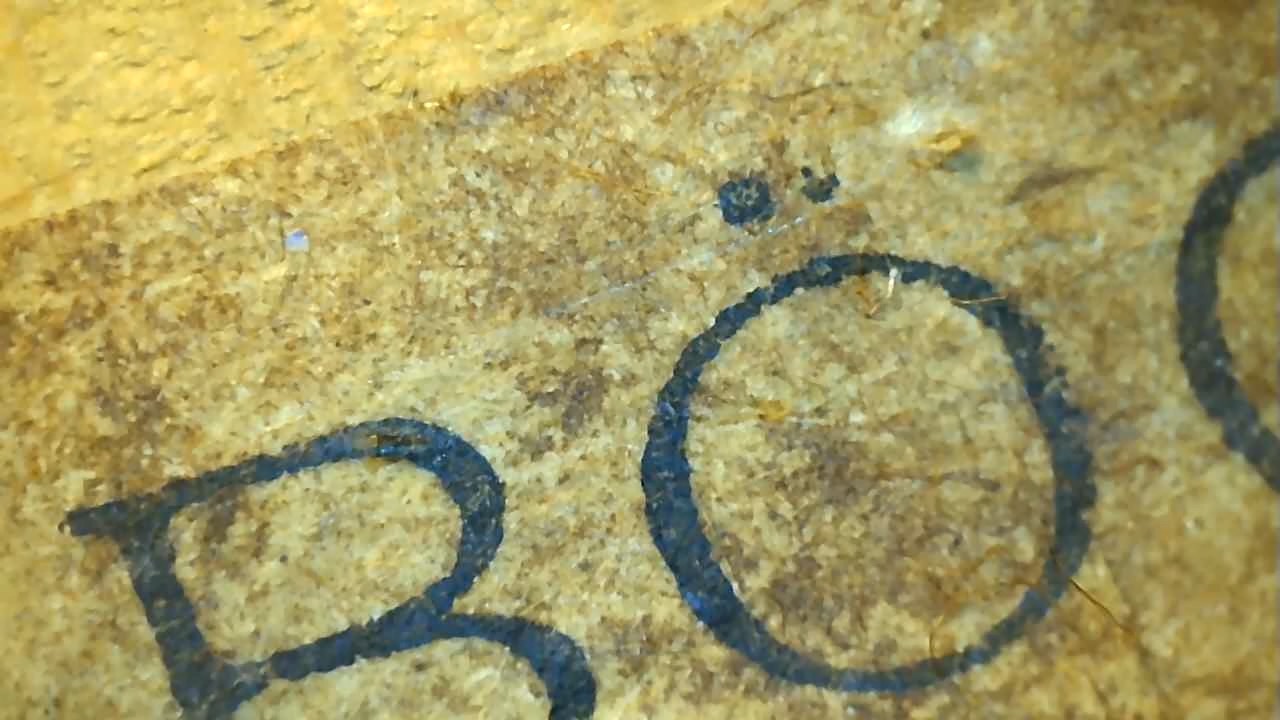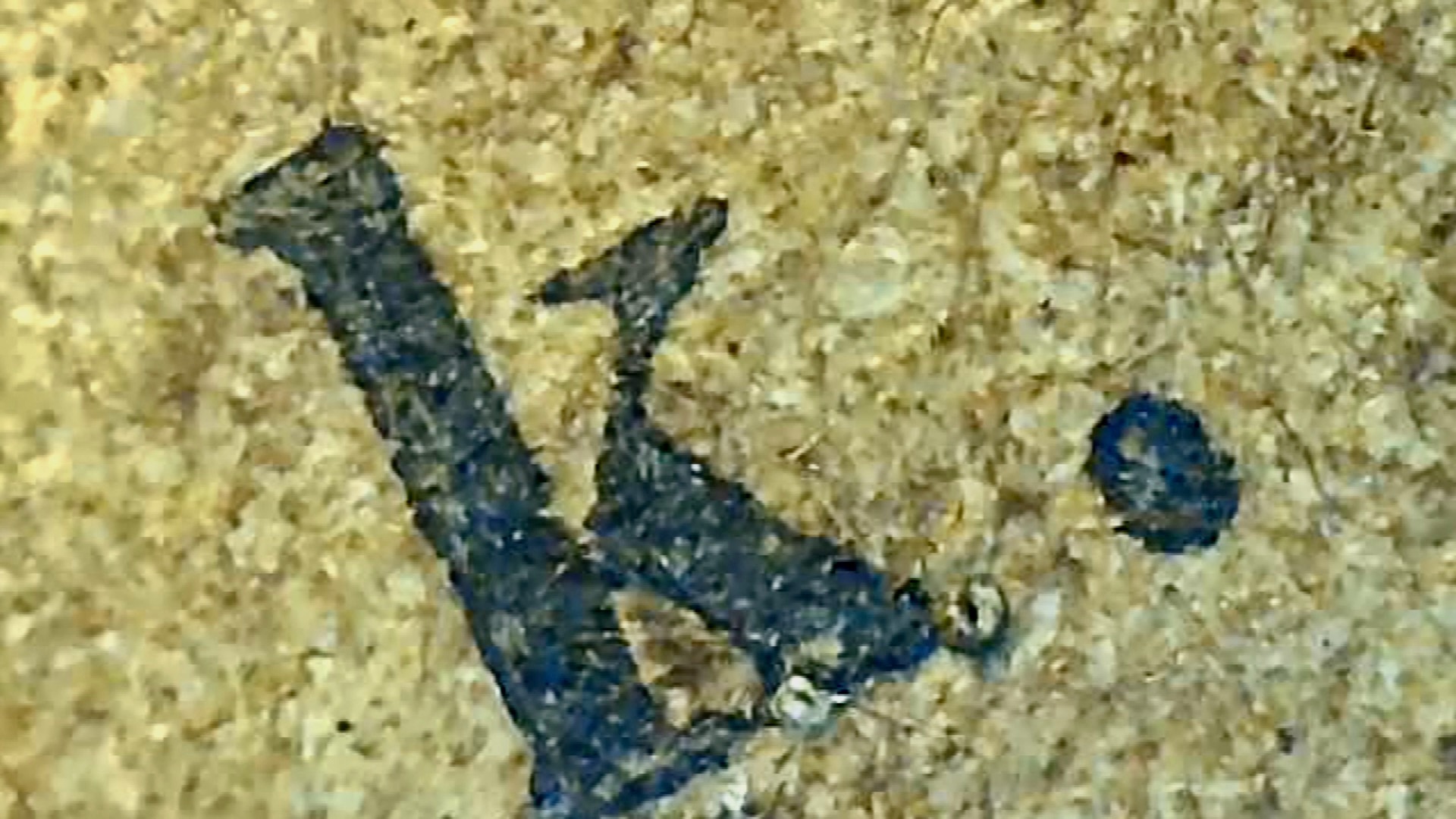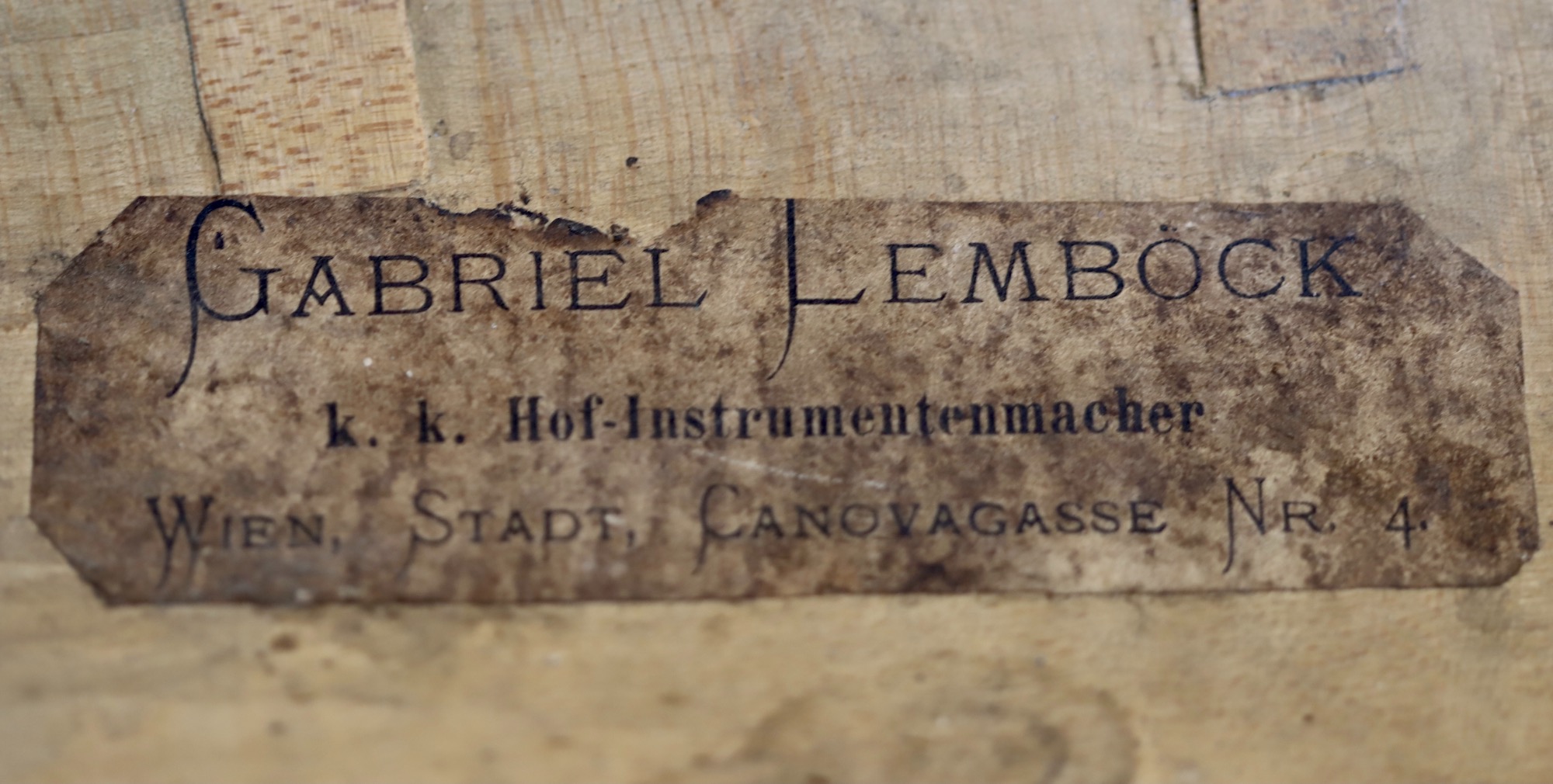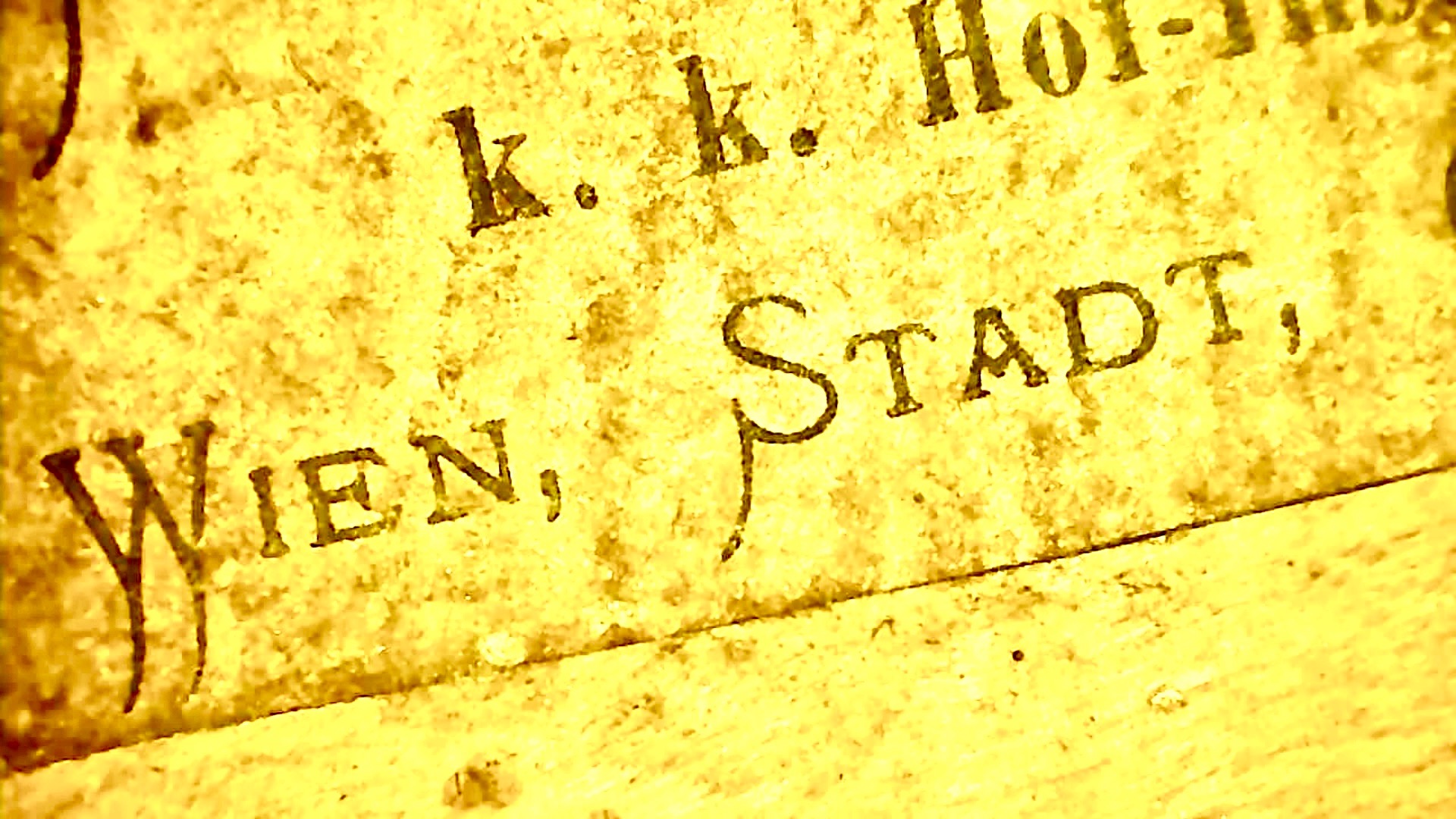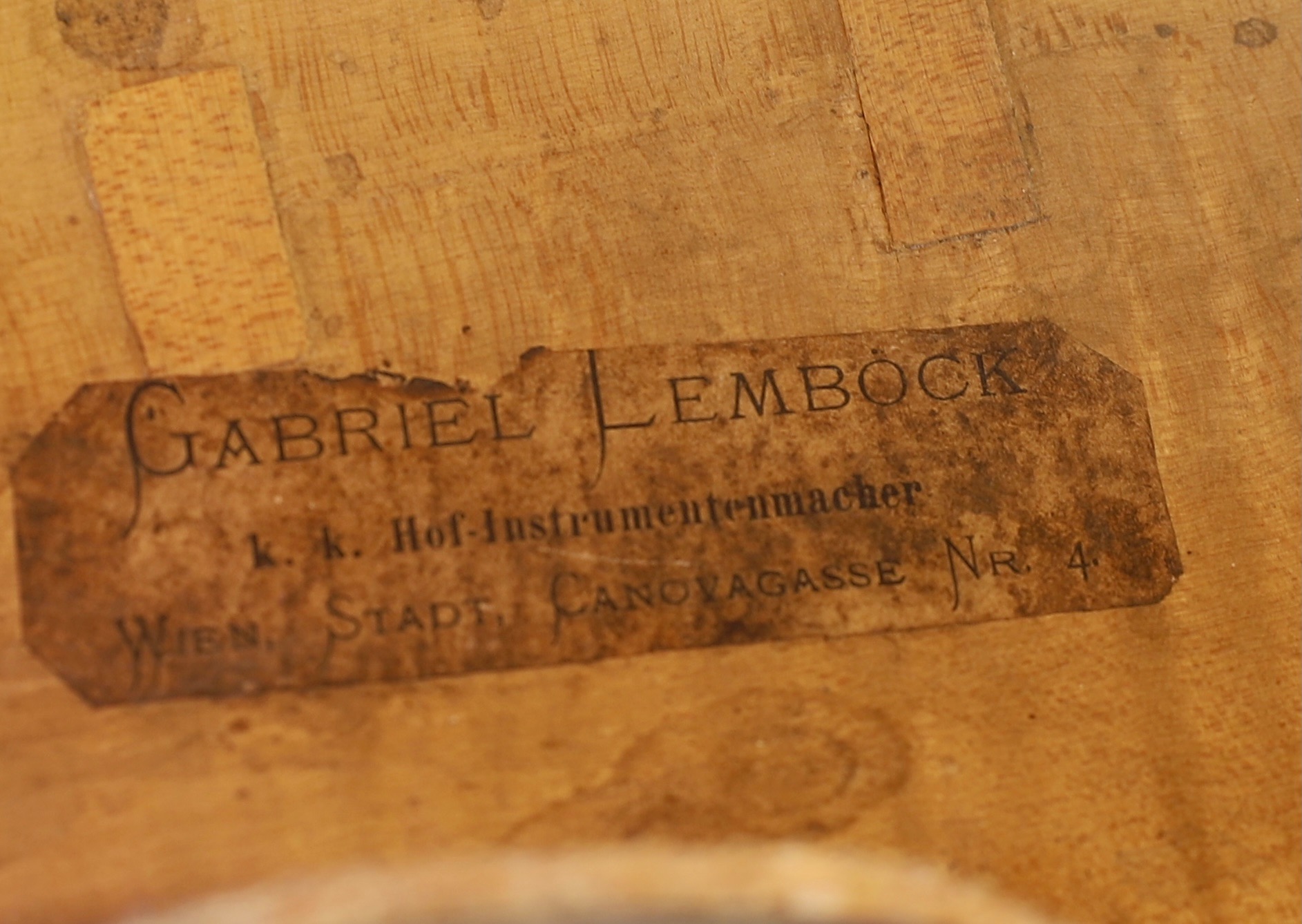
Es geht darum zu ermitteln ob es die 3 Schrifttypen dieses Zettels 1860 schon gegeben hat und ob es sich um ein Orginal-Zettel handelt oder er nachträglich frei erfunden wurde.
Der Zettel wäre auf alle Fälle gut gealtert geworden falls es sich um eine "Fälschung" handelt. Nur die tewas lieblose Zuschneidung des Zettels irritiert mich denn mein bringt ja eigentlich sowas mit etwas Stolz an.
Zur Schrift kann ich nichts sagen. Dazu werden sich die experten äußern (denke ich ...)
A decorative font with descending tails on the capital letters. The design is based on a popular typeface from the 1880s, mainly used for personal names on title-pages, advertisements and stationery.
Today, you can use it on invitation cards, menus and concert programs to give a fin-de-siècle impression. Accented letters for Western and Central European languages are included.
Welche "popular typeface from the 1880s" das ist, kann ich nicht sagen.
Bei deutschen Gießereien hießen Schriften dieses Stils zum Beispiel Antike Skelett (AG für Schriftguß, Bauer, Krebs, Stempel) Zierschrift 529 (Genzsch & Heyse) und Schweifschrift (C.E. Weber). Die sind allesamt undatiert. Ob es sie 1860 schon gab, kann ich nicht sagen.
Es ist auch durchaus möglich, dass das Etikett aus einem anderen Instrument stammt und sich dort nicht einwandfrei ablösen ließ, so dass man den oberen Rand beschnitten hat. Ich hatte auch einmal eine Geige, die mit einem Etikett ausgestattet war, das zwar ähnlich alt war, aber überhaupt nicht zum Instrument passte.
Ich hab schon deutlich ältere Instrumentenzettel kopiert und mich eine Weile damit befaßt. Es gab viele Fälschungen für Nachbauten von Instrumenten, oft erkennt man die an der Schrift. Der schlechte Beschnitt des hier gezeigten Zettels spricht eher für die Echtheit. Je älter die Zettel, desto schlechter gedruckt und beschnitten. Das waren sicherlich Drucksachen, die von Lehrlingen oder Aushilfen ganz schnell nebenbei mal gemacht wurden, die Qualität ist oft sehr schlecht. Das ist ganz drollig bei der Kopie, wenn man in der Druckmaschine die Walzen ganz dicht an die Schrift stellt, damit sie schmieren, wenn man zuviel Farbe verwendet, damit sie schön unsauber herumläuft um die Schrift, wenn man die Klischeevorlagen aus verschiedenen Schriften in arg schlechtem Satz zusammensetzt und dann am Klischee mit Hämmerchen, Sandpapier und anderem die Buchstaben noch so richtig kaputtmacht und zerdonnert. Es gibt Sammlungen von Instrumentenzetteln. Ich weiß nur nicht wo, denn die Instrumentenbauer bringen so etwas immer mit, wenn sie zu mir kommen. Aber man kann in diesen Sammlungen einiges zu den Schriften sehen, also was wann wo gedruckt wurde. Das hilft dann manchmal auch bei der Ermittlung zu Fälschungen.
Von 1860 kann aber der Zettel nicht sein, weil es da die Canovagasse in Wien noch nicht gab. Die wurde erst 1865 so benannt. Man müßte nachschauen, wie Zettel des Instrumentenbauers sonst aussahen. Vielleicht ist die Zeitschätzung nur um zehn Jahre verschoben. Gefälscht wurden später eher ältere Instrumente. Es kann freilich die Fälschung eines ungefähren Zeitgenossen sein, der kein K.u.k-Zertifikat hatte.
Was ich zuletzt produzierte, waren Zettel für sehr aufwendige Kopien aus dem frühen 18. Jahrhundert, also woran auch der Instrumentenbauer mit wissenschaftlicher Kooperation mehr als ein Jahr arbeitet. Als ich einen der vorliegenden Zettel des Instrumentenbauers sah, sagte ich sofort: Das ist 20. Jahrhundert. So industriell hat man vorher nicht gedruckt, und die Schrift gab es so sicherlich auch nicht, das sind die späten gestauchten Ober- und Unterlängen. Also Fälschung. Im Ergebnis war es ein Test des Instrumentenbauers, ob ich mich ein bißchen auskenne. Der gefälschte Zettel war von 1920.
Von 1860 kann aber der Zettel nicht sein, weil es da die Canovagasse in Wien noch nicht gab.
1870 wurde das neu erbaute Musikvereinsgebäude eröffnet und L.[emböck] übernahm. 1870 übernahm am 10.5. dieses Jahres im Erdgeschoss des Hauses, in der Canovagasse 4, ein Atelier.
Von 1860 kann aber der Zettel nicht sein, weil es da die Canovagasse in Wien noch nicht gab.
Was ebenfalls dagegen spricht, ist, dass das Musikvereinsgebäude an dieser Adresse erst 1870 eröffnete. Lemböck hatte dort ebenfalls ab 1870 sein Atelier.
Was mich irritiert:
1. Der Mann hieß Lemböck, auf dem Zettel steht Lembock. Im Netz finden sich auf Anhieb drei Instrumentenzettel, mit ö. Warum ist auf diesem Zettel kein Baujahr notiert? Das ist eigentlich nicht üblich.
2. Daß eine neue Schrift so schnell in Gebrauch kommt, ist wohl nicht oft vorgekommen. Dann noch für so einen schnell und unordentlich gemachten Zettel. Kommt das Instrument vielleicht aus Amerika, nicht aus Wien?
3. Und warum steht dort »Stadt«? Das steht auf den andern Zettel im Netz nicht. War das in Wien üblich? Gab es auch Wien Land?
vor 12 Minuten schrieb Martin Z. Schröder:
Da hast du nicht richtig gelesen: der Zettel ist deutlich mit ö. Die anderen Zettel sind alte Zettel vor 1872. Ab 1872 haben, glaube ich, seine Geschäftsführer unter seinem Namen produziert. Falls die Wiener Geigenbauer mir zurückschreiben oder ich etwas erfahre würde ich mich melden.
Und warum steht dort »Stadt«?
Das ist der Bezirk "(Innere) Stadt"
im alltäglichen sprachgebrauch sagt aber jeder wiener auch heute noch »ich fahr’ in die stadt«
Das war bei mir in Hamburg auch so, Wenn meine Muztter mit mir zum Einkaufen ins Hamburger Zentrum, das ja deutlich mit dem Wallring erkennbar ist, fuhren wir in "die Stadt" So setzt es sich in der Umgangssprache noich immer fort, dass die Stadteile außerhalb des Zenntrums außerhalb der historischen Stadtgrenzen liegen.